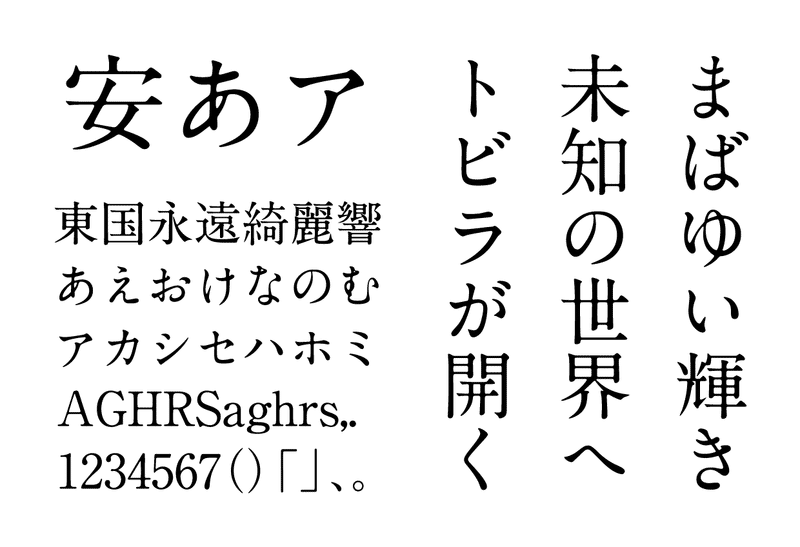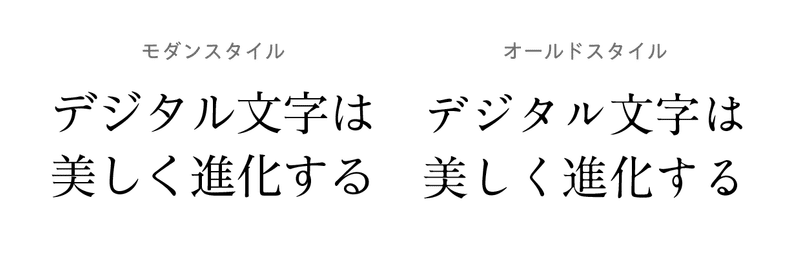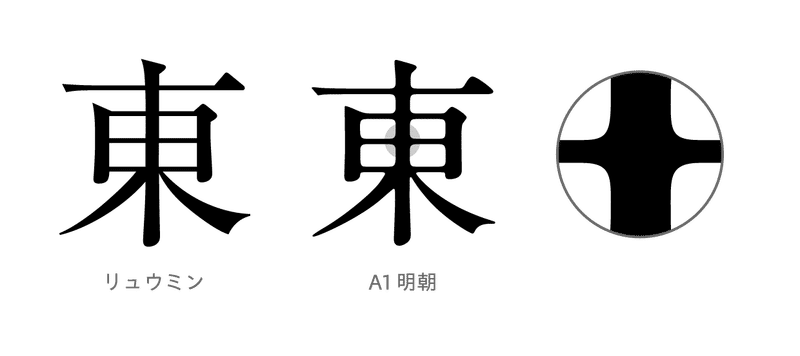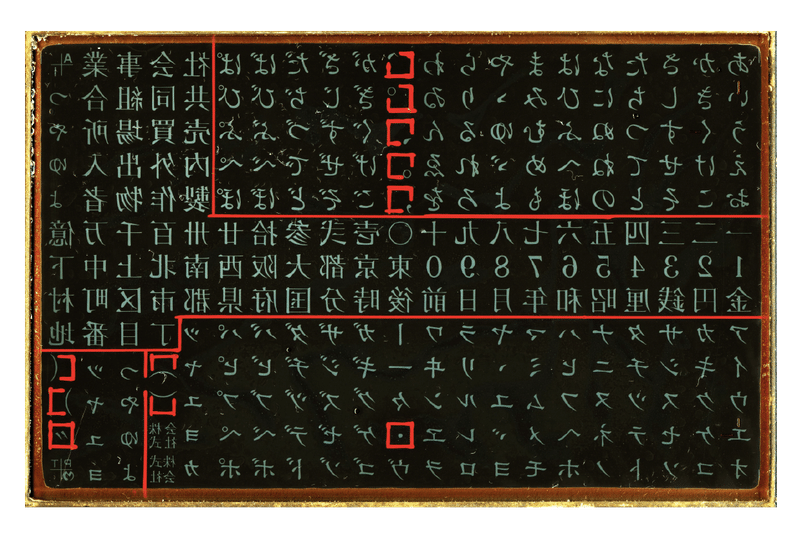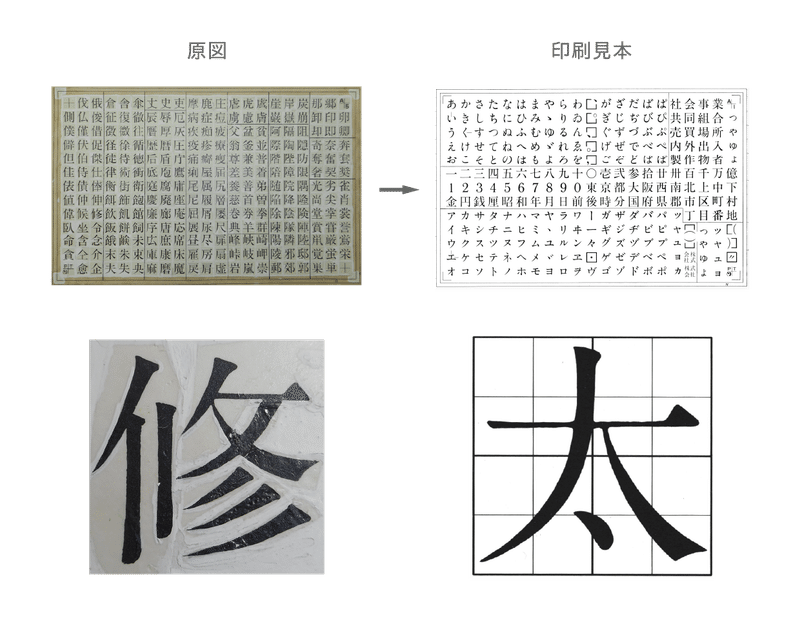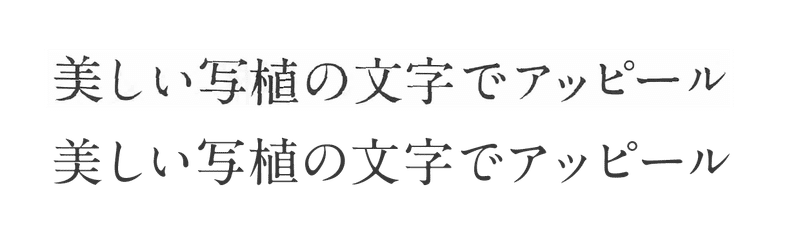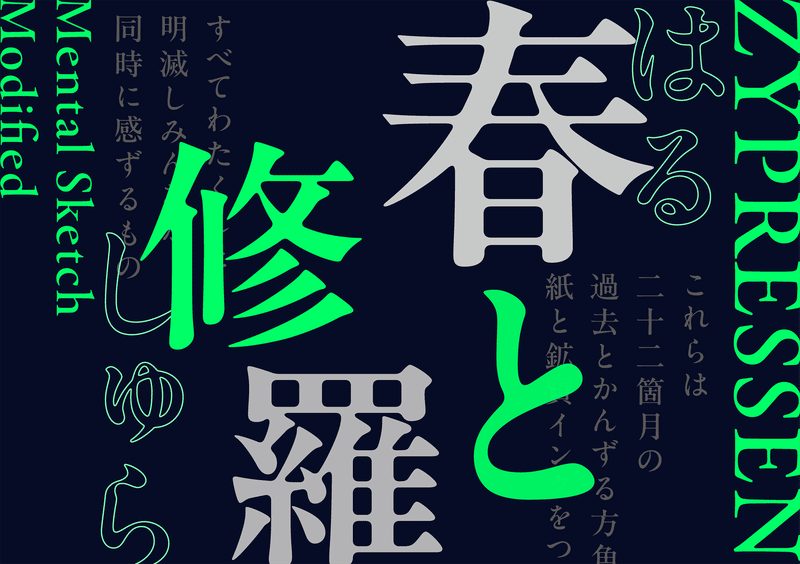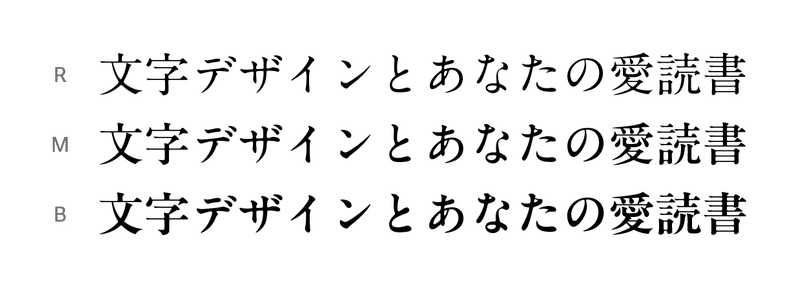
人気書体「A1明朝」の新ウエイト開発に迫る
モリサワのフォントライブラリで一二を争うほどの人気書体「A1明朝」が、この度3ウエイト構成の “A1明朝ファミリー” として新たにリリースされます!
「A1明朝」といえば、某有名アニメーション映画のタイトルに使われている “あの書体” として認識されている方は多いのではないでしょうか。長年のファンも多く、そのノスタルジックなたたずまいからデジタルフォントとして今もたくさんご愛用いただいている書体です。
今回はそんなA1明朝をもっと好きになってもらうために、書体の歴史からAP化・新ウエイト開発の裏側まで語り尽くします。
「A1明朝」の特徴
まずはA1明朝を初めて知った方のためにも、書体の特徴をおさらいしていきます。
A1明朝は、オールドスタイルの明朝体に分類されます。どこか整いすぎていない、ゆったりとしたカーブの漢字と流麗なかなの絶妙なバランスで、独特の味わいを持った書体です。
「オールドスタイル」の書体は、ふところが狭く、文字ごとのサイズや幅でより自然な筆書きに近い骨格を持っています。「モダンスタイル」の明朝体の「黎ミン」と比較してみると形も印象もガラッと変わりますね。
そして、A1明朝のデザインといえば、なんといってもこの “墨だまり” です。
他の明朝体にはあまりない処理として、先端や交差部分に角が丸くなったようなアールが施されているのが大きな特徴です。これによって、やわらかな印象と自然な温かみを感じさせる書体に仕上がっています。
この墨だまり、もともとは温かみを演出するための装飾ではなく、とある理由でこの形になっていたのを “再現” しているんです。その由来は60年前まで遡ります。
これまでのあゆみ
A1明朝が今の形に至った経緯は、印刷業界の歴史と深く関係しています。
1960年 写植用書体「太明朝体A1」リリース
A1明朝の元となる書体は、現在主な印刷技法となっているDTP以前、1960~1980年代の日本で主流となっていた「写真植字(以下、写植)」の時代に生まれました。写真植字機は、原字が映されたネガのガラス板(文字盤)の文字を光学的に印画紙に焼き付ける “写真で文字を組む機械” でした。
その写植用の書体として生まれ、A1明朝の前身となったのが「太明朝体A1」です。
そして、墨だまりの正体はまさにこの写植による印刷の特性にあります!
「太明朝体A1」は原図ではよりシャープなアウトラインですが、文字を光学的に印画紙に焼き付ける写植の特性により、印刷された見本では文字の交差部分ににじんだようなアール(角の丸み)がついています。
交差部分の丸みが写植の特性であるということは、「太明朝体A1以外にも写植で印刷された書体は墨だまりができていたのでは?」と思うかもしれません。もちろん他の書体でもこのような仕上がりのものはありましたが、一方で墨だまりの発生を避けるための “隅とり” の処理が施される書体もありました。
写植による印字では、レンズで拡大縮小して文字サイズを決めるだけでなく、レンズの角度調整によって長体や平体、斜体といった光学的にゆがめた像をつくる書体の加工が行われていました。また、写真のピンぼけを利用した “ボケ印字” や、レンズに紗をかけて文字のエッジを甘くしたりする細工も行なわれていました。
こういった写植由来のアナログな書体の加工のアイデアが、デジタルフォント化の際に原字デザインをそのままフォントにするのではなく、墨だまりも含めてA1明朝のデザインとして採用されるきっかけになったのかもしれません。
2005年 「A1明朝」としてデジタルフォント化
そして、2005年には「A1明朝」としてデジタルフォントがリリースされます。可読性を担保しつつ、柔らかな書体の雰囲気をより活かすために墨だまりを残し、柔らかく目に優しい文字組版を目指しました。
また、このタイミングで字形の修正のほか、かなは一回り大きくして潰れが起きそうな箇所を改善、漢字も偏と旁が極端にアンバランスなものが修正されました。これらは太明朝体A1に当時寄せられていたお客様の声から修正方針が決められました。
当時のお客様の声の中には「ちょっと太らせると、柔らかい良い感じになる」というコメントもありました。以降もA1明朝の太いウエイトを望む声はたびたび聞かれるようになり、ウエイト拡張のプロジェクトは密かに進んでいったのでした。
2023年 新書体「A1明朝(AP版) R/M/B」リリース
今回リリースされる「A1明朝」改め「A1明朝(AP版)」で新しくなった点を見ていきましょう。
1. ウエイト拡張
これまで単一ウエイトで提供されていた太さを「R」とし、新たに「M」と、さらに太い「B」が追加されました。
M、Bは墨だまりのにじんだ感じが目立ち、より温かみのあるデザインになっています。チラシやバナーでリッチさを出したいときや、より印象を強めたい場面でもご活用いただけそうです。
ちなみに、2005年リリースの「A-OTF A1明朝 Std」はウエイト表記が「Bold」になっているのに対し、2023年リリースの「R」が従来のA1明朝相当なのでご注意ください。
2. AP化
書体名にも「(AP版)」とあるように、和文・欧文ペアカーニングと最新のIVSに対応した AP版書体としてのリリースになります。
3. 欧文・記号デザインの刷新
AP版リリースの際に一部書体はデザインの調整や変更が行われており、A1明朝(AP版)で大きく変わったところとして、欧文・記号のデザインが新規で制作されました。
16世紀のフランスにルーツをもつローマン体に着想を得たクラシカルな骨格を持ち、オールドスタイルの明朝体に合わせたデザインにリニューアルされました。AP化にともなってスペーシングも調整されています。「和欧混植する際に欧文書体は別のフォントを使っていた」という方も、A1明朝の新しい欧文デザイン、一度試し打ちしてみてください。
新ウエイト開発の裏側
さらに詳しく制作舞台裏を語っていただくべく、A1明朝(AP版)の開発に関わったデザイナーを突撃しました!
デザイナーインタビュー
ー まずは、3人の分担について教えてください。
原野:既存のA1明朝のデータからウエイト拡張をしたのですが、私がMとBのウエイトの太さを決めました。主な担当範囲については、私がかな、小田さんに漢字の拡張をご担当いただきました。
池田:墨だまりがついていないアウトラインからの拡張だったので、私の方では太めたデータをお二人から引き継いで、小田さんにもご相談しながら墨だまりの加工をしていきました。
ー ありがとうございます。さっそくなのですが、原野さんのプロフィールの好きなフォントに「A1明朝」の記載があり、ぜひどんなところが好きかお聞かせください!
原野:そう言われるとうまくお伝えできるか自信がないのですが(笑)、個人的には静かだけど凛とした雰囲気があって、使われているときに主張しすぎずデザインの中になじむ、澄んだ空気のような透き通った感じのある書体だと思っています。大学時代はグラフィックデザインを専攻していたのですが、学生の頃から好きな書体で自分の作品にも使っていたので、モリサワに入社しようと思ったきっかけでもありますね。当時そういう雰囲気の書体を他に知らなかったのでいい書体だなと思っていました。
ー 当時からウエイト展開があったらいいと思うことはありましたか?
原野:そうですね、もう少しウエイトの幅があったらいいのになと思っていました。
ー 原野さんも待望のファミリー化が今回実現したということですね! ちなみに、ウエイトはどのように決めていったのでしょうか?
原野:ウエイトを決めたのは数年前になるのですが、当時のチームのメンバーにアドバイスもいただきながらリュウミンを参考にして、今のR・M・Bの太さになりました。ウエイトのジャンプ率としてはMはもう少し太くてもよかったかなと思う一方、A1明朝は静かなグラフィックや、堅実さを持たせながらも印象的な場面でさりげなく使われる書体だと感じているので、RとMは微妙な変化かもしれないですが、Mは「Rがもうちょっとだけ太かったらよかったのに」という場面に対応できるかもしれません。
原野:自分でA1明朝を使っていた時ももうちょっと太ければな……と思う場面がありました。そんなかゆいところに手が届く、ユーザーさんの「これくらいの太さがほしい」みたいなところにうまくはまればいいな、と思います。
ー ご自身の経験から、まさに使い手目線で決めていったということですね。
ウエイト拡張以外だと、今回のAP化にあたってどんな調整があったのでしょうか?
小田:既存のウエイトのRでは、私の方で漢字の横画の位置が悪いものや、はらいが跳ね上げたような形のものをよりA1明朝として相応しいデザインに修正しています。とはいえ、長年ご好評いただいている書体ですから、今回は改刻というよりは既存のデザインをなるべく尊重して微調整したというイメージです。2005年の写植の原図をデジタル化した時にもっと多くの修正がありましたね。
小田:微調整してもなお他の明朝体に比べるとアンバランスさがある書体なので、墨だまりがないとちょっと出来の悪い明朝体になってしまうけど、これが文字を邪魔せずついていることですごく味のある書体になっていると思います。墨だまりは役者で言ったら名脇役!
小田:やっぱりこの書体は墨だまりがいいですね。大きさも絶妙。私は昭和の人間なのでA1明朝は昭和レトロな書体だと思ってます(笑)。でも、古くは見えない。洗練されてもいるし、ほっとするような暖かさもあるし……
だから多くの人に愛されている書体になっているのかな、と思います。
あとがき
今回はファミリー化・AP版のリリースを記念して、「A1明朝」について深掘りしました。
デジタル化の際にあえて墨だまりをつけるというのは、写植の原図に施された隅とりとは全く逆の発想ですが、その墨だまりを逆手に取ってデザインの一部としたフォントがあるというのは筆者的 “フォント沼” ポイントでした。